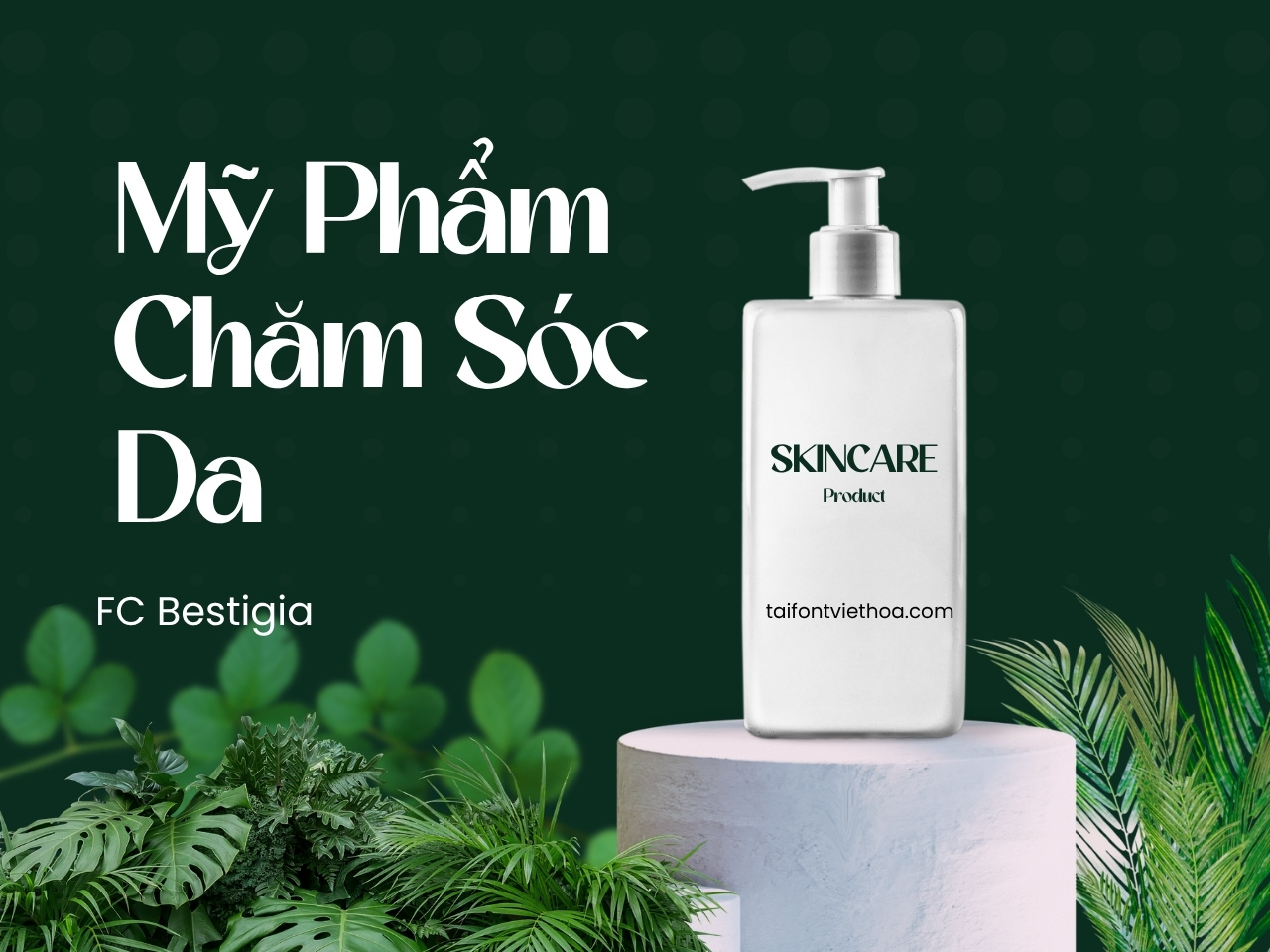
Giới thiệu về font Bestigia và phiên bản Việt hóa
FC Bestigia là một phiên bản Việt hóa độc lập từ font gốc “Bestigia” – một phông chữ serif ấn tượng được thiết kế bởi Creatype Studio. Khác biệt rõ rệt với phiên bản “1FTV VIP Bestigia”, bản FC Bestigia do cộng đồng Font Chuẩn thực hiện đã được hiệu chỉnh riêng để phục vụ tối ưu cho người dùng tiếng Việt, đồng thời vẫn giữ nguyên tinh thần cổ điển pha hiện đại của thiết kế gốc. Font sở hữu các đường nét thanh mảnh, sang trọng nhưng đầy cá tính – rất phù hợp cho các dự án liên quan đến thời trang, thương hiệu cao cấp và xuất bản.
Phiên bản Việt hóa FC Bestigia do cộng đồng Font Chuẩn thực hiện, đảm bảo chất lượng hiển thị tiếng Việt mượt mà, đồng bộ về cấu trúc và thẩm mỹ với bản gốc. Các dấu thanh tiếng Việt được căn chỉnh tỉ lệ hợp lý, giữ nguyên sự sang trọng và cá tính đặc trưng của font gốc. Font này đã được taifontviethoa.com sưu tầm, chọn lọc và giới thiệu lại nhằm đáp ứng nhu cầu về một serif chuyên nghiệp, dễ ứng dụng vào các dự án thực tế trong thiết kế tại Việt Nam.
Đặc điểm thiết kế và khả năng ứng dụng
FC Bestigia gây ấn tượng bởi các nét chữ có chân rõ ràng, độ tương phản cao giữa các đường nét dày và mảnh, cùng với tỷ lệ chữ cân đối và các đầu nét được xử lý mượt mà. Thiết kế này mang đến cảm giác vừa cổ điển vừa đương đại, tạo nên phong cách sang trọng và dễ dàng thu hút thị giác. Font có bộ chữ hoa rất nổi bật, phù hợp làm tiêu đề, kết hợp cùng chữ thường nhẹ nhàng để tạo ra bố cục hài hòa.
FC Bestigia là lựa chọn lý tưởng cho các lĩnh vực như thời trang, mỹ phẩm, xuất bản, nhiếp ảnh, thiết kế bao bì và branding cao cấp. Ngoài ra, font cũng rất thích hợp trong thiết kế quảng cáo, thiệp cưới, sự kiện hoặc các ấn phẩm yêu cầu sự trang nhã và chuyên nghiệp.